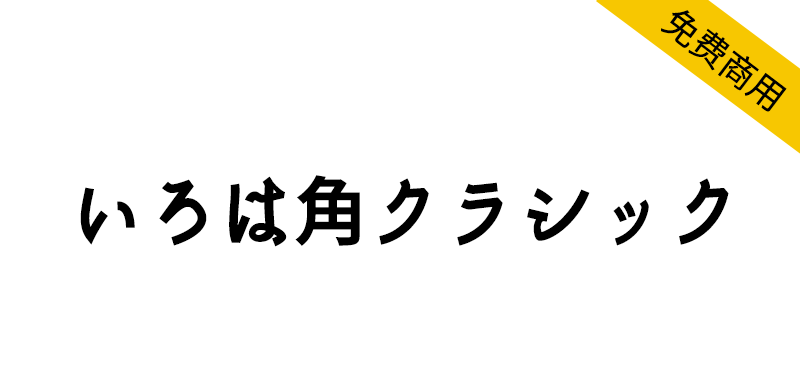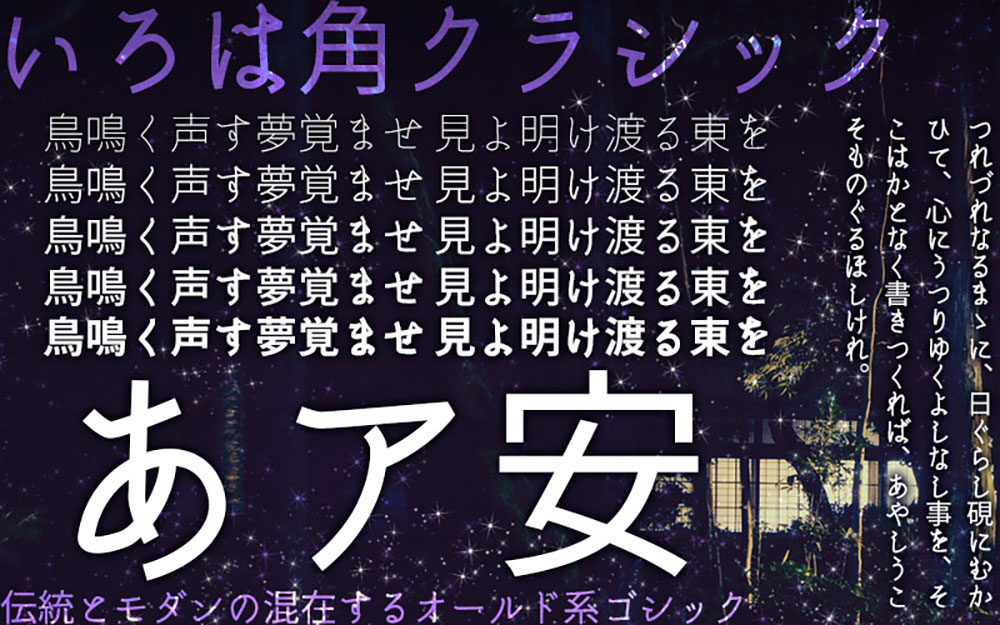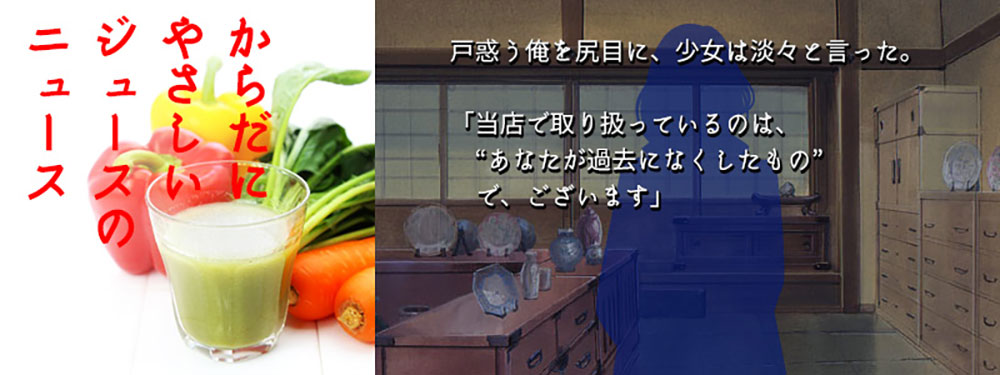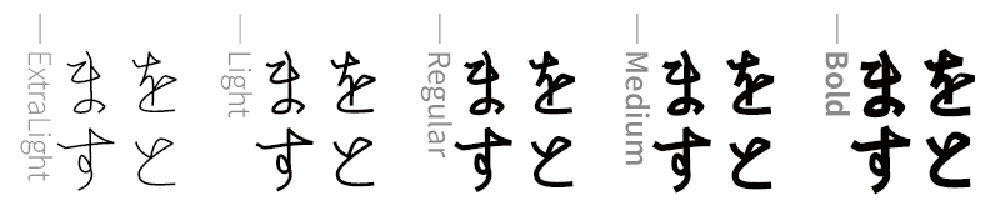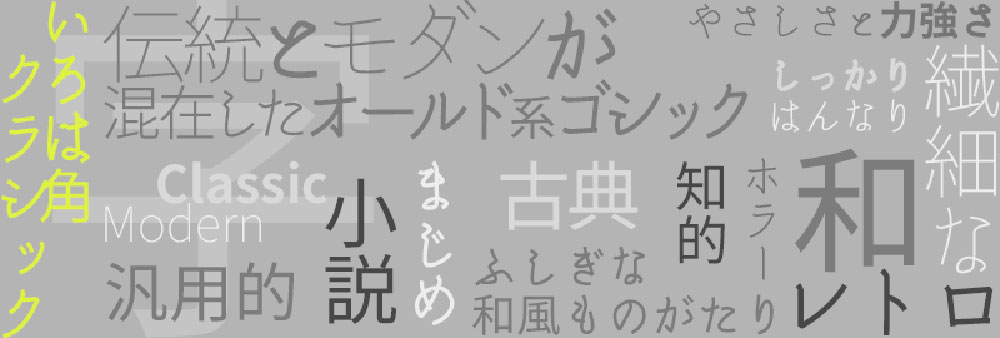
【いろは角クラシック】基于思源真黑体,融合了老式与现代元素
いろは角クラシック是一种修改字体,基于思源黑体的衍生字体思源真黑体(源真ゴシック),并具有原始的平假名、片假名和一些其他符号。这是一种易于使用的字体,结合了老式的字体和现代元素,5个字重。
源ノ角ゴシックの派生フォントである『源真ゴシック(自家製フォント工房/MM様)』の漢字を用い、ひらがな・カタカナ・その他一部記号をオリジナルにした改変フォントです。古風な字形と、現代的なシャープさを合わせ持った、使い勝手の良いフォントです。ウェイト5種。